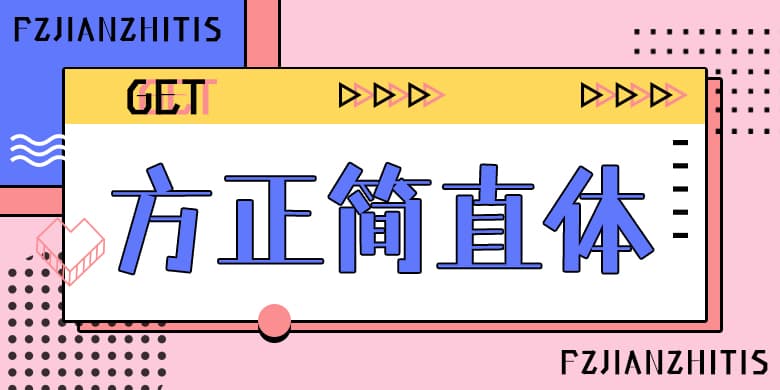
品牌:方正字库设计师:倪初万发行时间:2021字库编码:大陆简体(GB2312-80)分类:创意字体字体属性:精品字
《简直体》契合了宜家在中国所发育的现代生活市场,它不以简单、粗暴和血脉喷张示众,而是强调文字的整体感、节奏感和条理性;它理性地将横画的细线合理妥协地运用在软笔画的适当位置上,实验性地解决了汉字因笔画不同所造成的白度均衡性问题;它主张下笔肯定有力,以更简约的方式传承文字的书写感;它以干净、利落、脆的执拗,彻底抛弃了曲线,让字库的数据量降至更低,为客户的使用提供方便。